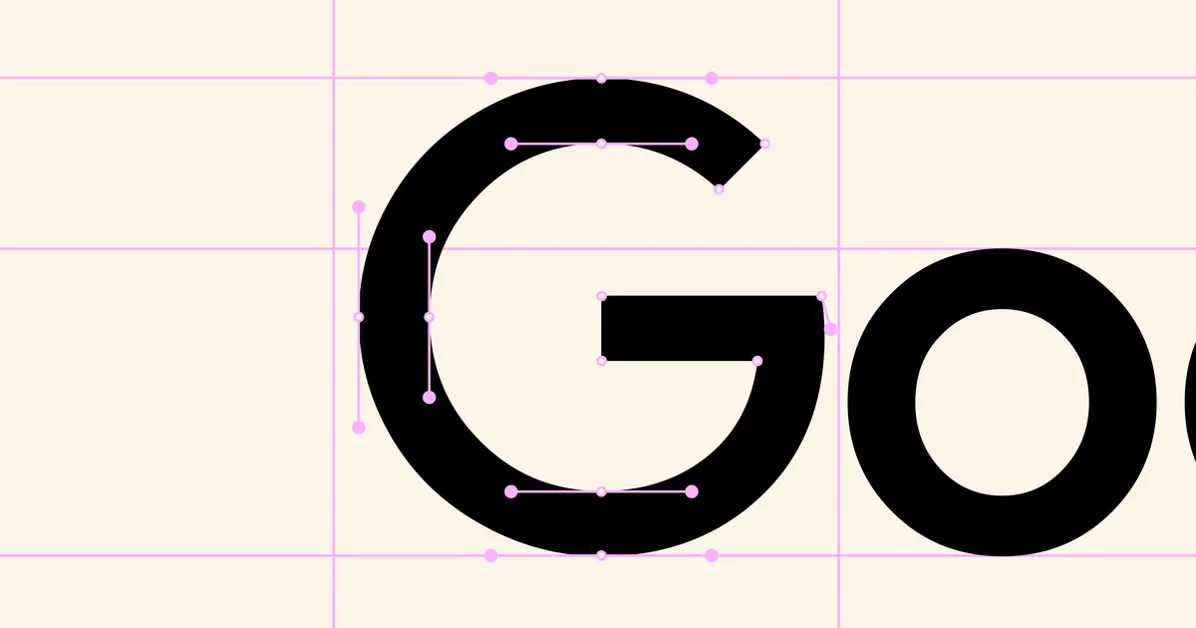
Google Sans Flex 폰트, 디자인은 좋지만 웹 성능은?
Google Sans Flex 폰트 공개와 함께 웹 페이지의 성능 문제가 제기됨
사용자들은 웹 페이지 로딩 속도 저하, UI/UX 문제를 지적하며 불만을 표출함
폰트 자체의 디자인보다는 마우스 커서 디자인, 웹 페이지 전반의 디자인 철학에 대한 논의가 주를 이룸
웹 페이지 성능 저하의 원인
Google Sans Flex 폰트 자체보다는 웹 페이지의 과도한 자바스크립트 사용, SPA(Single Page Application) 방식의 문제점이 지적된다. 구체적으로, 페이지 로딩 속도 지연, 뒤로 가기 버튼 작동 오류, 스크롤 시 버벅임 등 사용자 경험을 저해하는 요소들이 나타났다. 따라서 웹 페이지 최적화가 시급하다.
디자인 철학에 대한 상반된 시각
폰트 디자인 자체에 대한 긍정적 평가와는 별개로, 마우스 커서 디자인과 같은 세부 요소에 대한 비판이 제기되었다. 반면, Google의 디자인 철학에 대한 옹호적인 의견도 존재하며, 특히 Google Pixel 폰의 디자인을 긍정적으로 평가하는 의견도 있었다. 결과적으로, 디자인은 주관적이며, 사용자 경험을 고려해야 한다.
폰트 선택의 어려움과 대안
자신만의 폰트를 제작하는 개발자의 경험을 통해, 폰트 선택의 어려움이 드러났다. 구체적으로, 폰트의 개별적인 특징에 대한 불만족, 시간 소모적인 작업 과정 등이 언급되었다. 따라서, Guguru Sans Code와 같은 대안 폰트를 시도해 볼 수 있으며, 오픈 소스 폰트를 활용하는 것도 좋은 방법이다.